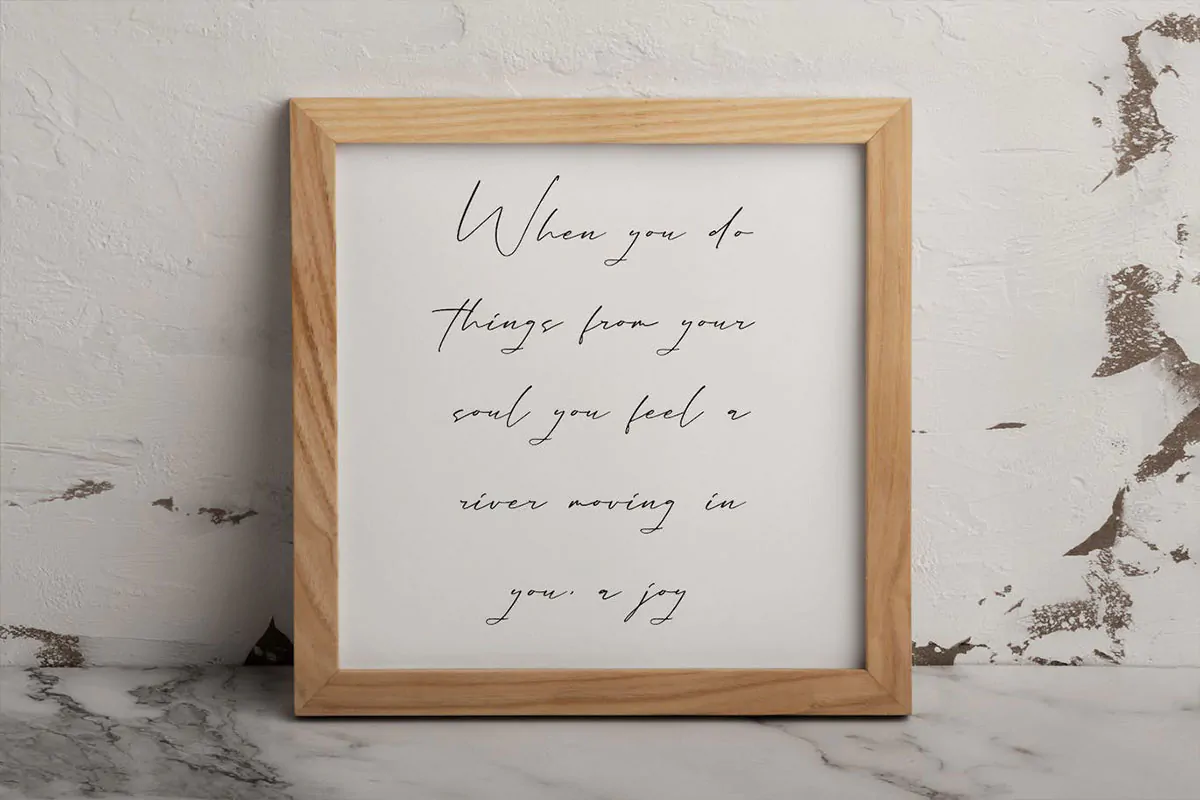
فونت امضا دستنویس شیک Bernathia Andalissa
فونت امضا دستنویس شیک
فونت امضا دستنویس شیک Bernathia Andalissa یک قلم فوق العاده زیبای انگلیسی است که میتوانید از آن در طرح و پروژههای مختلف همچون طراحی پوستر، کارت ویزیت، بروشور، کاور آلبوم موسیقی، بسته بندی محصولات و … استفاده کنید.